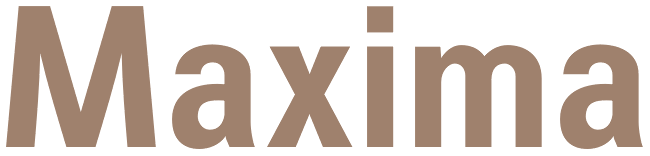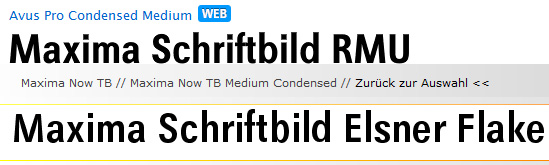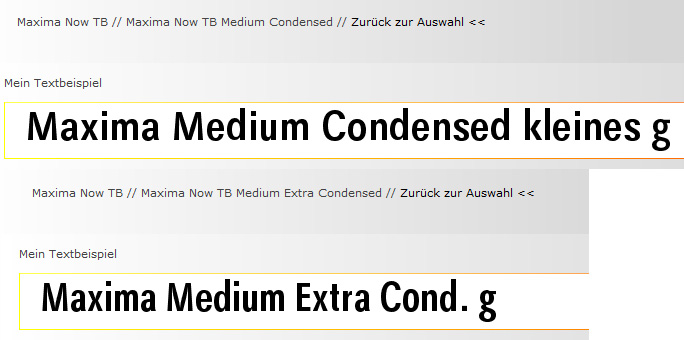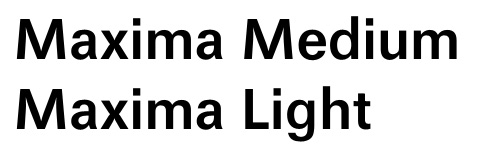
Pendants und Fragen zur Maxima und Xheighter
Ich habe mir vor ca. 1 Jahr mal die Maxima in den Schnitten Light und Medium angeschafft.
Ich benötige jetzt aber noch einen schmalen Schnitt und habe diesen bisher leider nur in fett gefunden, jedoch nicht in Medium.
Außer folgenden:
Aber das kleine "g" sieht anders aus, als bei meiner Light und normalen Medium.
Ich bin zwar am überlegen, die Schnitte "medium condensed" und "extra condensed" zu kaufen, möchte aber ein einheitliches kleines "g" haben.
Die Maxima gibt es von unterschiedlichen Herstellern, hier z.B. von EF für 19 €, ich glaube, da hatte ich meine beiden Schnitte (mit dem "richtigen" g) auch gekauft für je 19 €:
Davon gibt es aber nur "Bold Condensed" und kein anderes Condensed, wie z.B. Medium.  :-(
Daher die Frage: Ist jemandem ein Condensed-Schnitt der Maxima (evtl. unter anderem Namen?) mit dem kleinen "g" bekannt, welches meine normal breite Maxima hat? Oder kann man das kleine "g" nach dem Kauf ändern? Würde mir dabei evtl. jemand helfen?
Außerdem bräuchte ich zur Herstellung zweier (!) Aufkleber die Schrift "Xheighter Bold Condensed":
Hier müßte das kleine "a" und "r" angepaßt werden, das kleine "t" oben abgeschrägt und die senkrechten Enden des kleinen "s" etwas verkürzt. Das würde ich noch selbst hinkriegen, denke ich.
Bei der Maxima ist es anders, die nutze ich ziemlich oft. Daher würde ich dafür auch wieder bezahlen.
Sollte jemand die Xheighter besitzen, würde ich mich auch sehr freuen, wenn mir derjenige die 2 benötigen Texte als Vektorgrafik anlegen und zusenden würde.
Ich habe heute den ganzen Tag probiert, die Buchstaben im HighLogic Font Creator zu importieren, aber es wird leider immer ungenau und sieht nicht gut aus. Ich wollte die Konturen nachzeichnen, aber da ich die Vorlage nicht als "Hintergrundlayer" zum Nachzeichnen eingefügt bekommen habe, ging das nicht. Es wurde immer automatisch ein Buchstabe angelegt beim Import.
Den nachzeichen hat nicht geklappt, da dann die Breiten nie genau wurden. Irgendwann nach mehreren Stunden habe ich dann resigniert.
Daher würde ich mich über Hilfe sehr freuen.
Meine Maxima
Maxima Cond. mit "falschem" g:
Xheighter Bold Condensed (Original-Vorlage):
Xheighter Bold Condensed Screenshot:
In der Pro-Version ist das andere g drin ...
TB deutet in diesem Fall darauf hin, dass es um eine Textschrift geht, im Gegensatz zu TH für Headline. Das ist/war die gängige Bezeichnung bei TypoArt-Schriften. Die Rechte dieser Schriften sind jetzt bei Elster + Flake, die den oben genannten Shop auch betreiben. Die ›Now‹-Version, die du gekauft hast, ist eine von EF modernisierte Überarbeitung der original Maxima. Warum da aber das Brillen-g drin ist statt dem anderen kann ich dir nicht sagen - evtl. weil das von Gerd Wunderlich ursprünglich so geplant war  :-?
Die mitunter etwas eigenartige Schriftschmiede RMU hat - so glaube ich zumindest gesehen zu haben - auch Schnitte von der "Ost"-Helvetica (so wurde die Schrift in DDR-Setzerkreisen gern genannt) digital herausgebracht, aber unter einem anderen Schriftnamen, der mir partout nicht einfällt ...
Darauf ein Pils ... en Plakat? Ok, das t ist etwas anders ... Reicht Pilsen Plakat vielleicht trotzdem?
MfG und Prost
Vielen Dank für den Tip! Dafür entsprechen a, r und s eher meinen Wünschen. Das t kann ich mir noch selbst anpassen.
Ich werde es morgen mal testen, bin dafür jetzt zu müde.
In der Pro-Version ist das andere g drin ...
Tatsächlich. Das würde aber nochmal 59 € mehr kosten. 59 € nur für ein "g"? Das finde ich doch etwas heftig.
Für 40 € würde ich mir die Schrift ja kaufen. Aber 99 € nur wegen eines kleinen "g"?
Noch dazu scheint es ein Sonderzeichen zu sein, da auf dem Platz des "g" ja das mit dem Kringel abgelegt ist.
Das müßte ich dann auch erst wieder manuell ändern. Und wie gesagt sind mit 59 € dann doch etwas zu happig für ein anderes kleines "g".
Ich finde gerade die "Holperigkeit" der EF-Schrift gut. Wenn nur das "g" stimmen würde, täte ich sie mir ja kaufen.
... und die Helvetica ist die berühmtere Univers.
Solche Spitznamen fundieren ja meistens nicht auf genauer Formen-Analyse. Alle drei (+ AG) sind sich doch sehr ähnlich und nur in Details zu unterscheiden.